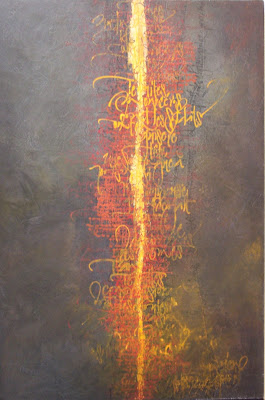
Il y a quelques mois, au lieu d'enduire mon panneau de médium en blanc cassé, j'ai voulu essayer un effet de porte étroite et travailler à partir d'une matière sombre. J'ai d'abord creusé un léger sillon vertical puis posé une bande verticale et irrégulière en jaune indien et orange de cadmium pour la saturation de la couleur. La couleur sombre est ensuite venue de part et d'autre, en léger relief. Je m'approchais d'une sensation, mais elle n'était pas encore définie. Mon regard croisait cette surface avec sa fente lumineuse, mais je ne savais pas vraiment ce qu'il y avait derrière. Il n'y avait qu'à attendre. . . qu'à attendre le livre, le texte, le pré-texte qui approfondirait le sujet. C'est un ensemble de textes, le seul recueil de poèmes publiés par Nicolas Bouvier qui s'est présenté. Un an auparavant, j'avais vu une exposition de ses photos à la Bibliothèque d'Etude de ma ville, et j'avais indéfinissablement été touchée par leur humanité.
J'ai choisi un texte, "D'un plus petit que soi" qui commence par cette mélopée nocturne, :
"Termes nocturnis
Termes obscuriceps
Termes taprobanis
..."
J'ai modelé discrètement les surfaces sombres pour donner de la profondeur à la nuit et monté la vibration orange en commençant par du caput mortuum et en descendant la gamme de valeurs jusqu'à l'orange de cadmium en surface. J'ai superposé les écritures, les textures en un serpent qui s'enroule autour de la fente centrale. Personnellement je vois un mouvement à la fois descendant et ascendant. C'est ce que j'ai voulu, je suis incapable de dire si c'est perceptible.
C'est un tableau qui est polysémique, qui veut permettre de multiples projections.C'est aussi le cas du texte originel. Selon la distance que je choisis, il peut raconter des histoires intérieures, ou bien à l'opposé, des histoires descriptives, narratives, au choix de celui qui regarde. Toutes celles que je me raconte sont vraies. Je perçois rarement les vérités uniques.
Avant ce tableau, j'avais peint celui-ci, sur le même texte. J'en avais juste traduit un moment donné.
Termites : 60x40
D'un plus petit que soi : 25x25
Cette "fissure" lumineuse est superbe.